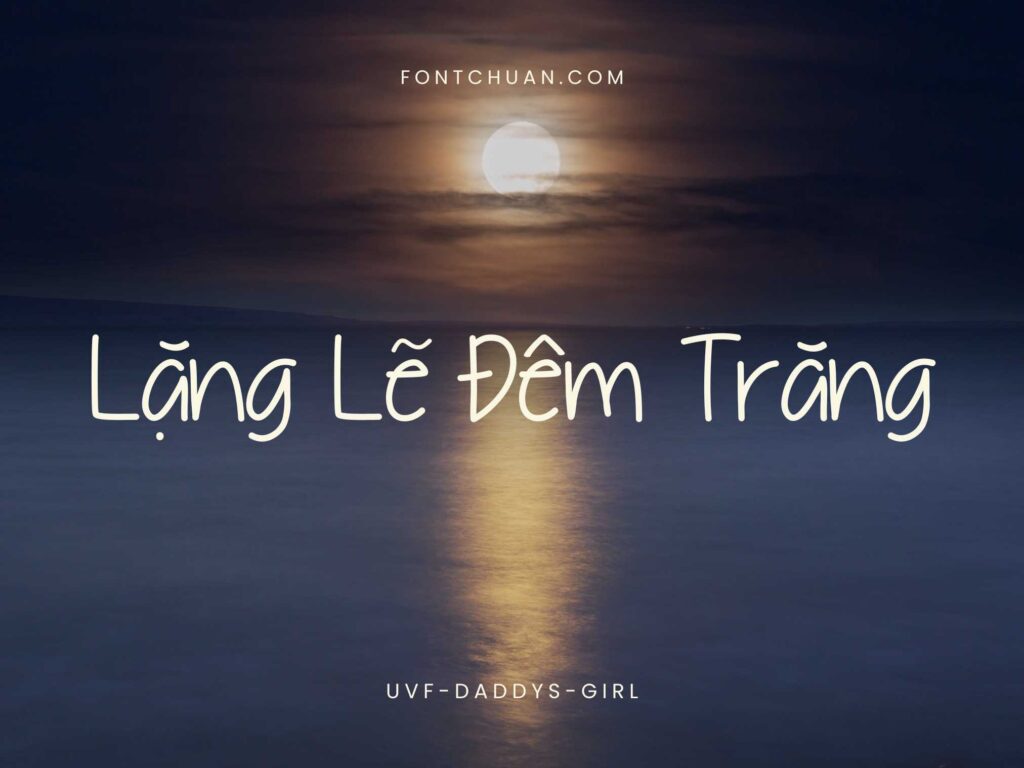
Font UVF Daddysgirl Việt Hóa
UVF Daddy’s Girl là một font chữ viết tay đáng yêu, mang phong cách nữ tính và tinh nghịch. Với các đường nét mềm mại và uyển chuyển, font này tạo cảm giác thân thiện và ấm áp, phù hợp cho các thiết kế như thiệp mời, bao bì sản phẩm, logo và các ấn phẩm dành cho trẻ em. Font này được sưu tầm và đăng bởi thành viên của Font Chuẩn.